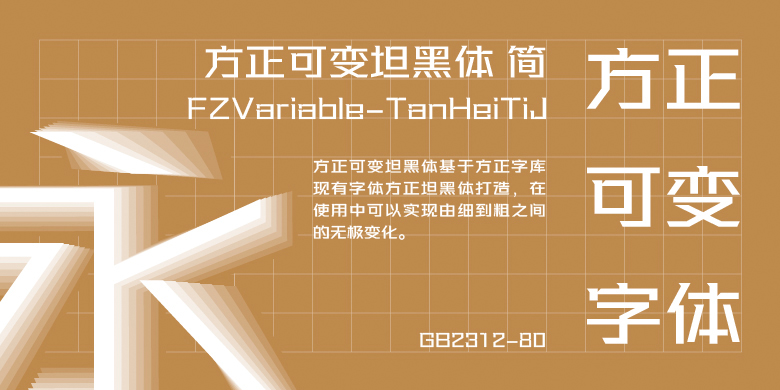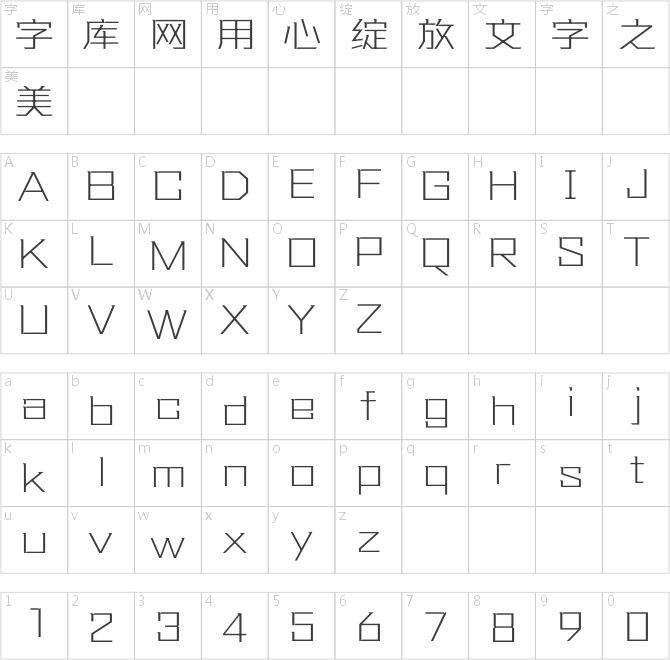
方正可變坦黑體 簡 詳情頁
字體名稱: 方正可變坦黑體
方正可變坦黑體支持文字粗細無級調節,設計師通過調整字重軸(Weight)的變化,可以實現字形的平滑連續的細微調整,滿足不同版式的設計需求。 坦黑體“坦” 其解釋為平而寬廣、直率、沒有隱諱,這款字體通篇筆畫皆為直線組成,表現最純粹的氣質,中宮外擴,字形飽滿,并且字型的細節處都有三角形的切角,使得整體的感受力量穩重而不顯臃腫。